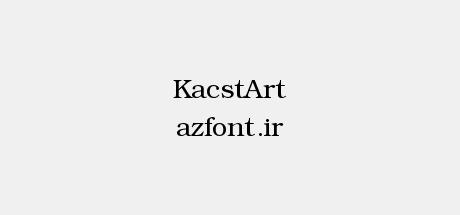
KacstArt
فونت زیبای رایگان KacstArt
قلم زیبای KacstArt از سری قلم های بسیار زیبا برای تایپوگرافی و لوگو تایپ می باشد.این قلم در وزن KacstArt و توسط Arabic design by Kourosh Beigpour, Latin design by Eben Sorkin, engineering by Lasse Fister and Khaled Hosney طراحی و منتشر شده است.